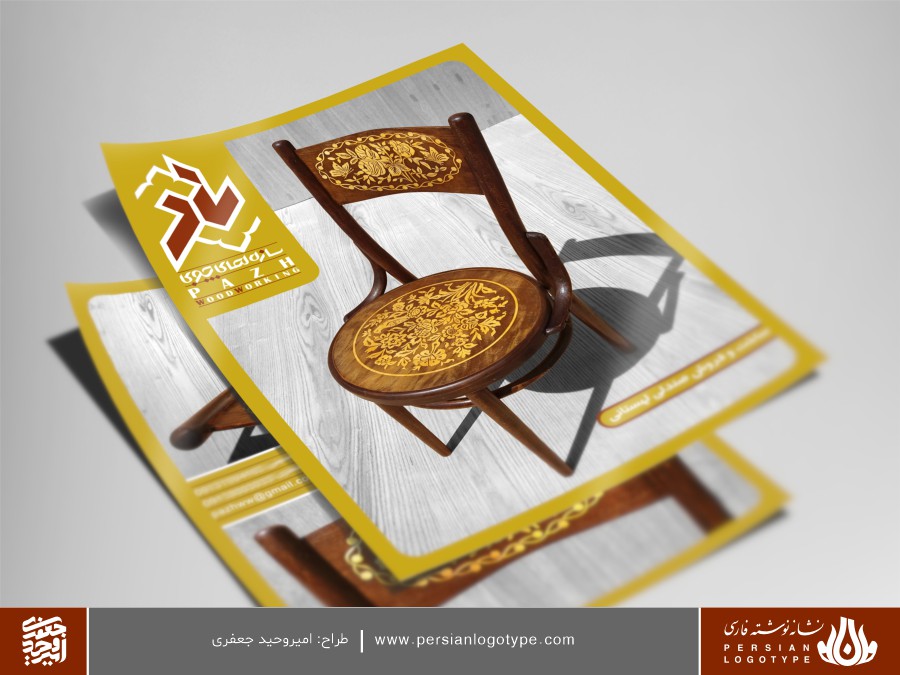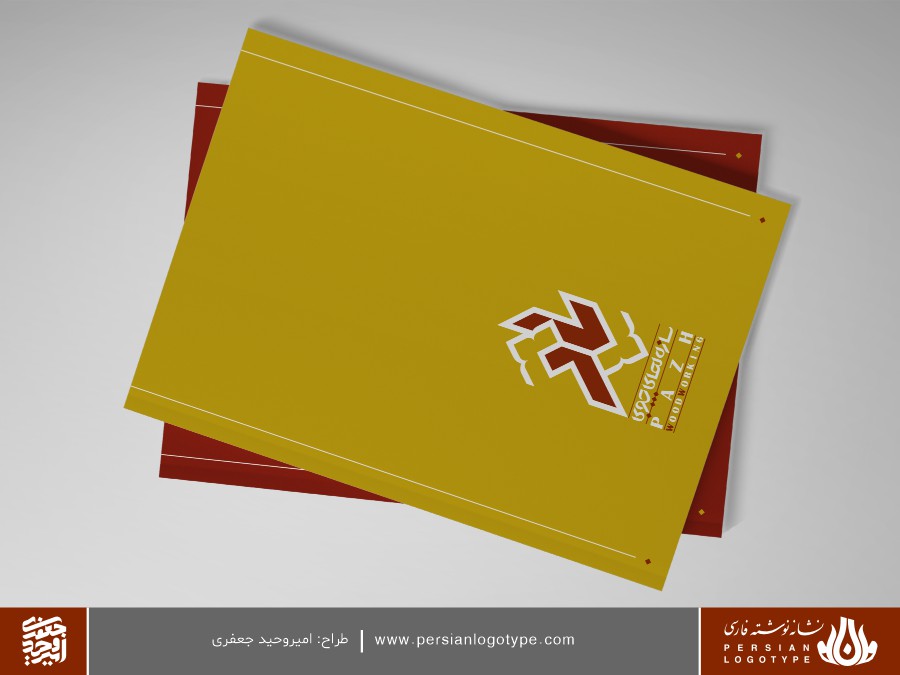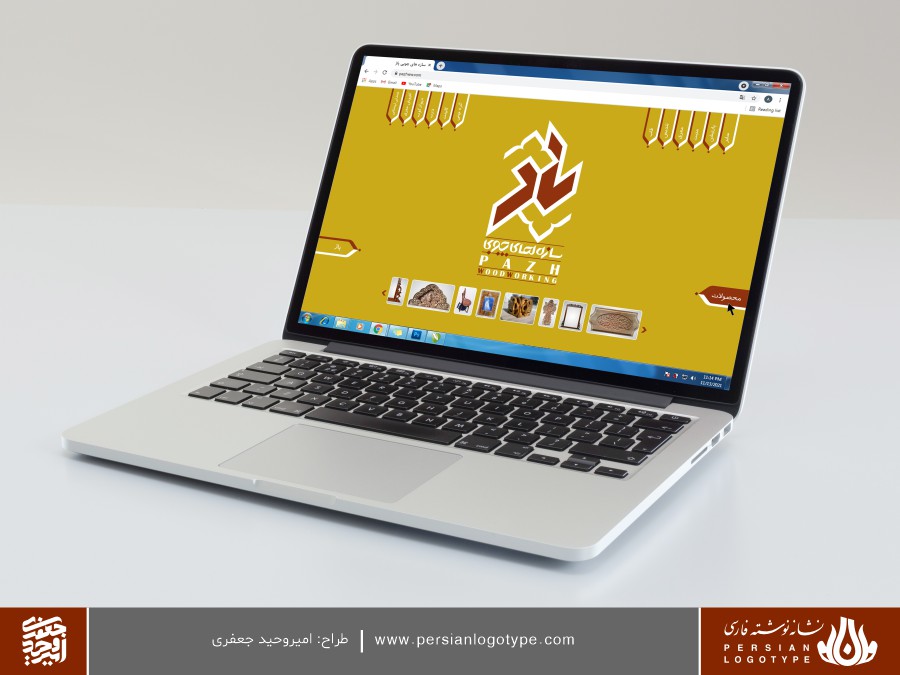
طراحی لوگوتایپ فارسی سازه های چوبی پاژ
طراحی و تولید انواع محصولاتی که عمدتا بر پایه چوب است و نیز ارائه خدمات و ساخت سازه های چوبی قابل استفاده در طراحی داخلی و خارجی ساختمان، مبلمان شهری، وسایل کاربردی و… در حوزه فعالیت برند سازه های چوبی پاژ قرار دارد. خط مشی اصلی این برند طراحی محصولاتی با حفظ هویت اصیل ایرانیست که علاوه بر داشتن زیبایی، متناسب با کاربرد و نیاز روز طراحی شده باشند. برای نمونه می توان از طراحی و ساخت درب ها و پنجره های قواره بری اسلیمی نام برد که بر اساس اصول حرفه ای نجاری سنتی انجام شده، یعنی تمامی آلت ها (قطعات ریز چوبی) به صورت کام و زبانه و بدون استفاده از چسب به هم متصل شده اند. در عین حال نیز با بهره گیری از فناوری روز، محدودیت های گذشته و اساتید این فن را بر طرف کرده و ابداعاتی نظیر قواره بری دو رو، حذف تیره اصلی، استحکام و دقت بیشتر و… را ایجاد کرده است.
پنجره های قواره بری اسلیمی
آلت های پنجره قواره بری اسلیمی
واژه پاژ برگرفته از نام روستایی در حومه شهر مشهد و محل تولد شاعر حماسه سرای ایرانی، حکیم ابوالقاسم فردوسی است. پس از بررسی ساختار حروف واژه پاژ و ظرفیت های بصری آن به جهت طراحی و با توجه به زمینه فعالیت برند و اهدافش، در طراحی این نشانه نوشته فارسی، نقش غنچه گل اسلیمی مورد استفاده قرار گرفت که از لحاظ معنایی هم بر زیبایی دلالت داشته و هم دارای هویت ایرانی است. ضمن اینکه طراحی ساده شده و نوگرایانه آن، علاوه بر این که بازتاب دهنده خط مشی طراحی و تولید بر اساس کاربرد و نیاز روز است، از منظر طراحی و ترکیب بندی نیز مسئله وجود نقاط زیاد در واژه را تبدیل به نقطه قوت کرده و باعث ایجاد سادگی و ترکیب بندی قوی و زیبا در این نشانه نوشته شده است.
نقش غنچه گل اسلیمی ساده شده در طراحی لوگوتایپ پاژ
گریدبندی در طراحی لوگوتایپ سازه های چوبی پاژ
طراحی زیرعنوان یا سابتایتل برای لوگوتایپ پاژ
لوگوها معمولا با توضیحاتی چند کلمه ای همراه می شوند که می تواند شامل نام کامل برند و یا توضیح مختصری از زمینه فعالیت برند باشد. به این توضیحات اصطلاحا سابتایتل (Subtitle) یا زیرعنوان گفته می شود. برای زیرعنوان می توان از فونت های رایج استفاده کرده و یا اینکه طراحی جدیدی مختص به آن انجام داد تا لوگو را در استفاده های مختلف گرافیکی همراهی کرده و شکل زیباتر و حرفه ای تری به آن بدهد. زیرعنوان «سازه های چوبی» برای لوگوتایپ «پاژ» به صورت اختصاصی و در هماهنگی با آن طراحی شده است.